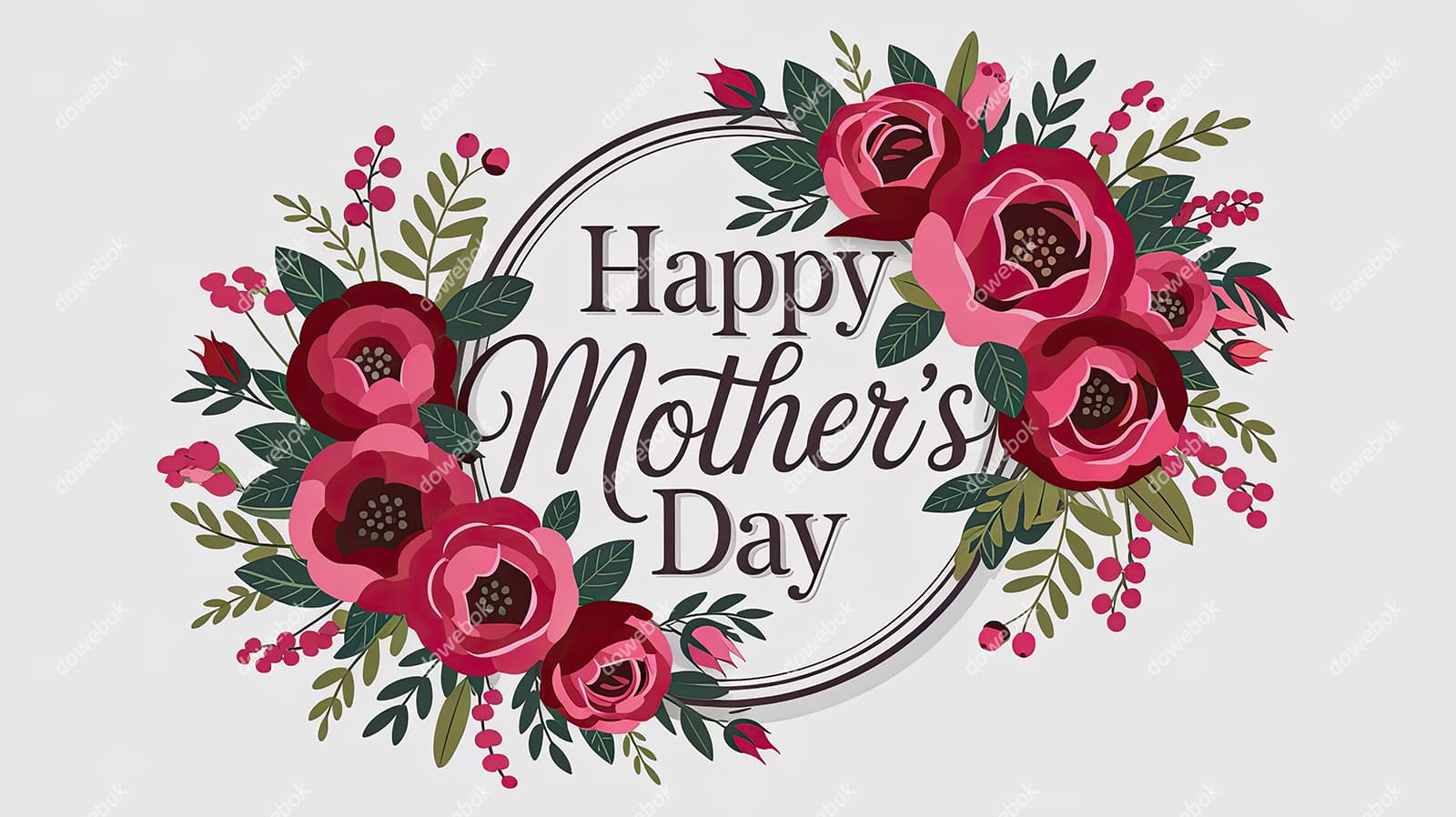
这是一款由花朵和 Happy Mother’s Day 字母设计母亲节图片素材,图片以浅灰色为背景,中央有圆形图案,里面写着 “Happy Mother’s Day”,字体优雅。圆形外环绕着精美的花环,由鲜艳的红色花朵、翠绿的叶子和红色小浆果组成,色彩对比鲜明,充满生机。整体设计简洁而温馨,传递出对母亲的美好节日祝福,氛围浓厚且温暖。